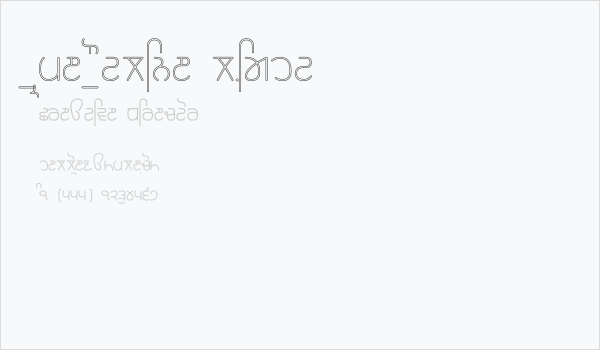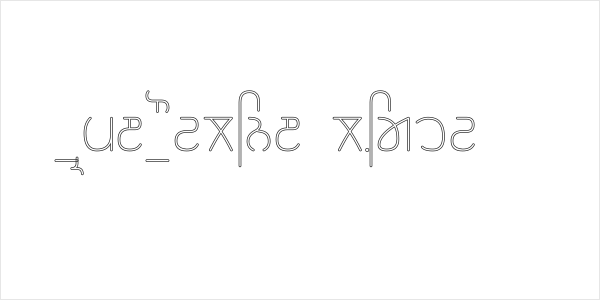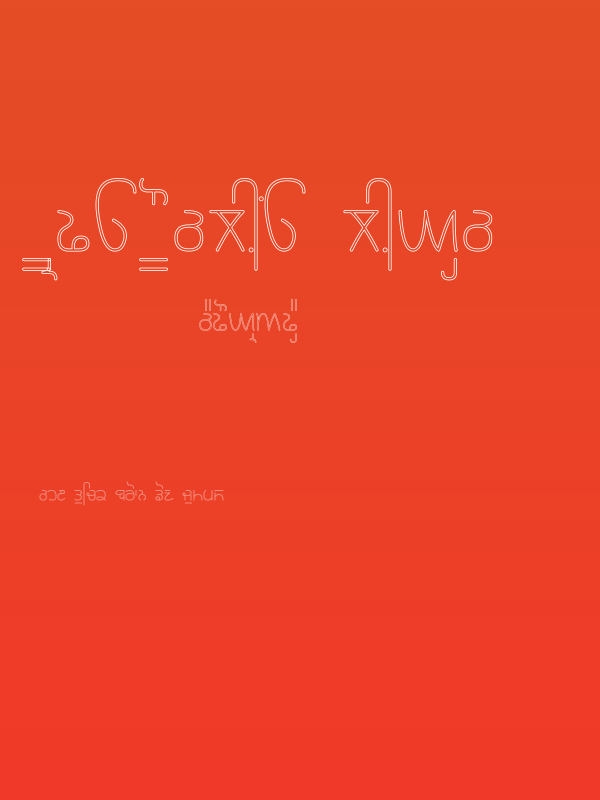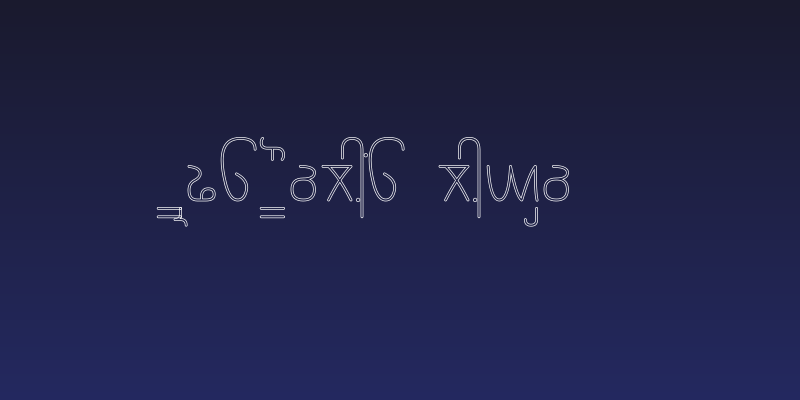
Rupe Outline Light Font
| Caso d'uso | Logos, Posters, Artistic Designs |
| Progetti proposti | Ideal for creative projects such as posters, logos, and artistic designs where a unique and modern look is desired. |